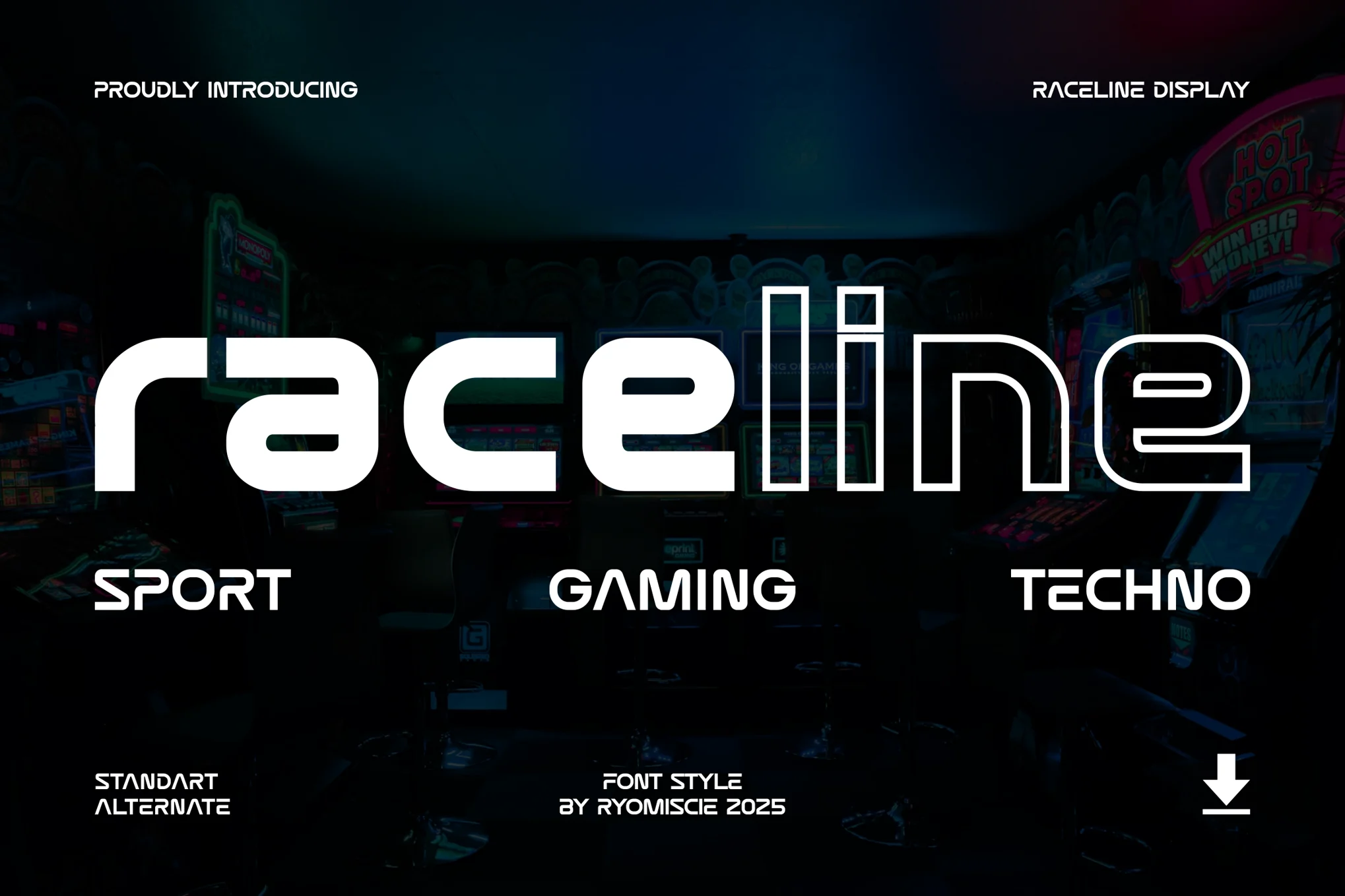
🏁 فونت Raceline – قدرت، سرعت و جسارت در طراحی
Raceline یک فونت نمایشی مدرن، بولد و پرانرژی است که با سبک جسورانه و طراحی خاص خود، انتخابی بینقص برای پروژههایی است که نیاز به حضور قدرتمند دارند. این فونت بهویژه در طراحی لوگو، چاپ روی تیشرت، برندهای ورزشی و دنیای بازیهای دیجیتال و eSport میدرخشد.
💼 ویژگیهای کلیدی:
- فونت نمایشی جسور و مدرن – مناسب برای تیترها، برندینگ و طراحیهایی که باید دیده شوند
- حروف بزرگ و کوچک + نسخههای جایگزین (Alternate) – انعطافپذیری بیشتر در ترکیب و چینش
- کاربرد وسیع – از طراحی تیشرت گرفته تا بستهبندی محصولات ورزشی یا پوسترهای گیمینگ
⚡ مناسب برای:
- طراحی لوگو و برندهای فعال
- محصولات چاپی مثل تیشرت، پوستر، لیبل و بستهبندی
- پروژههای Esport، بازیهای رایانهای و گرافیک حرکتی
- و هر فضایی که نیاز به یک فونت پرقدرت و مدرن دارد
Raceline نهتنها نمایشی پرانرژی دارد، بلکه با نسخههای مختلف فایل و امکانات جایگزینی حروف، آزادی عملی کامل برای خلق ترکیبهای گرافیکی جذاب به طراح میدهد. این فونت برای کسانی طراحی شده که میخواهند تأثیر بگذارند، نه فقط طراحی کنند.